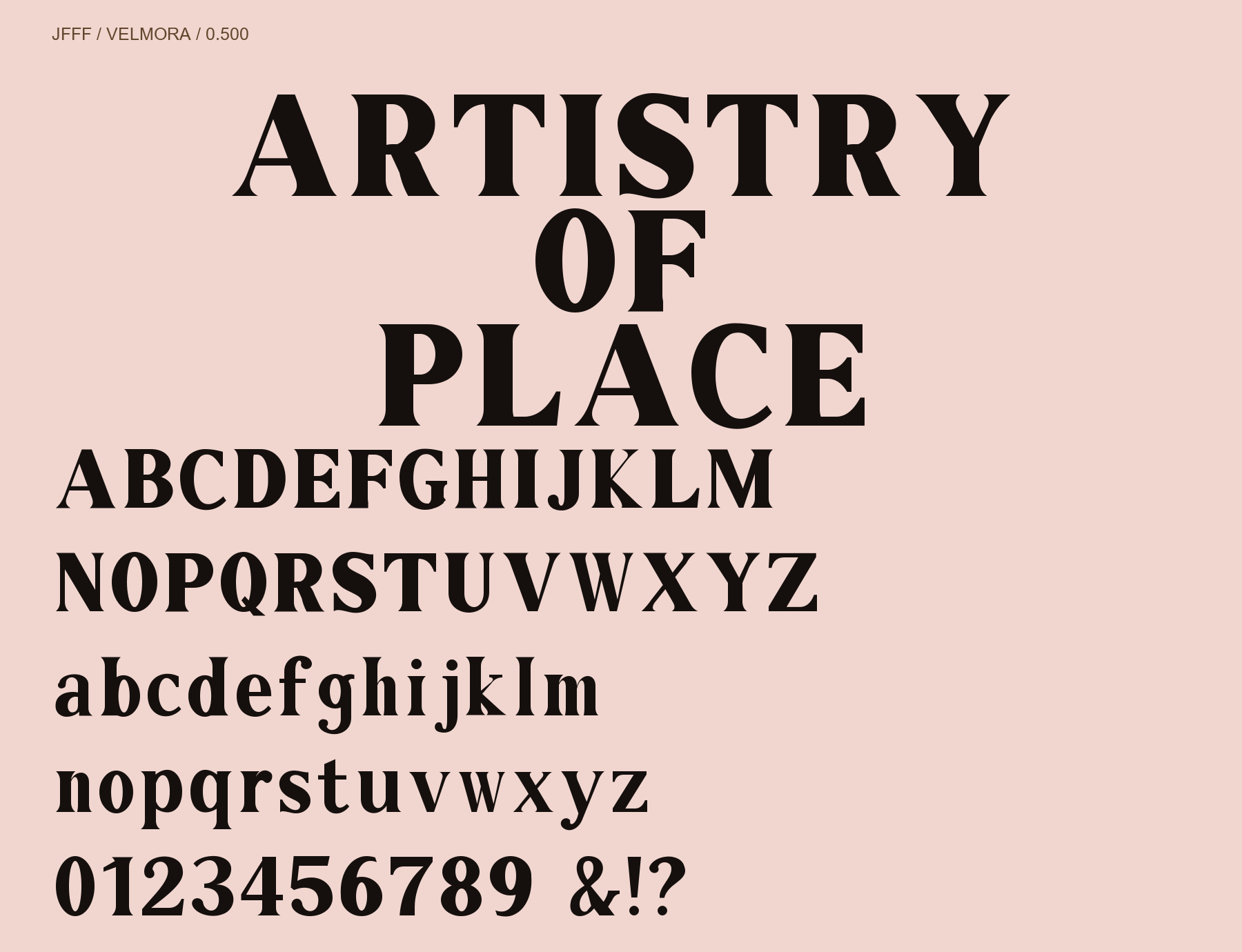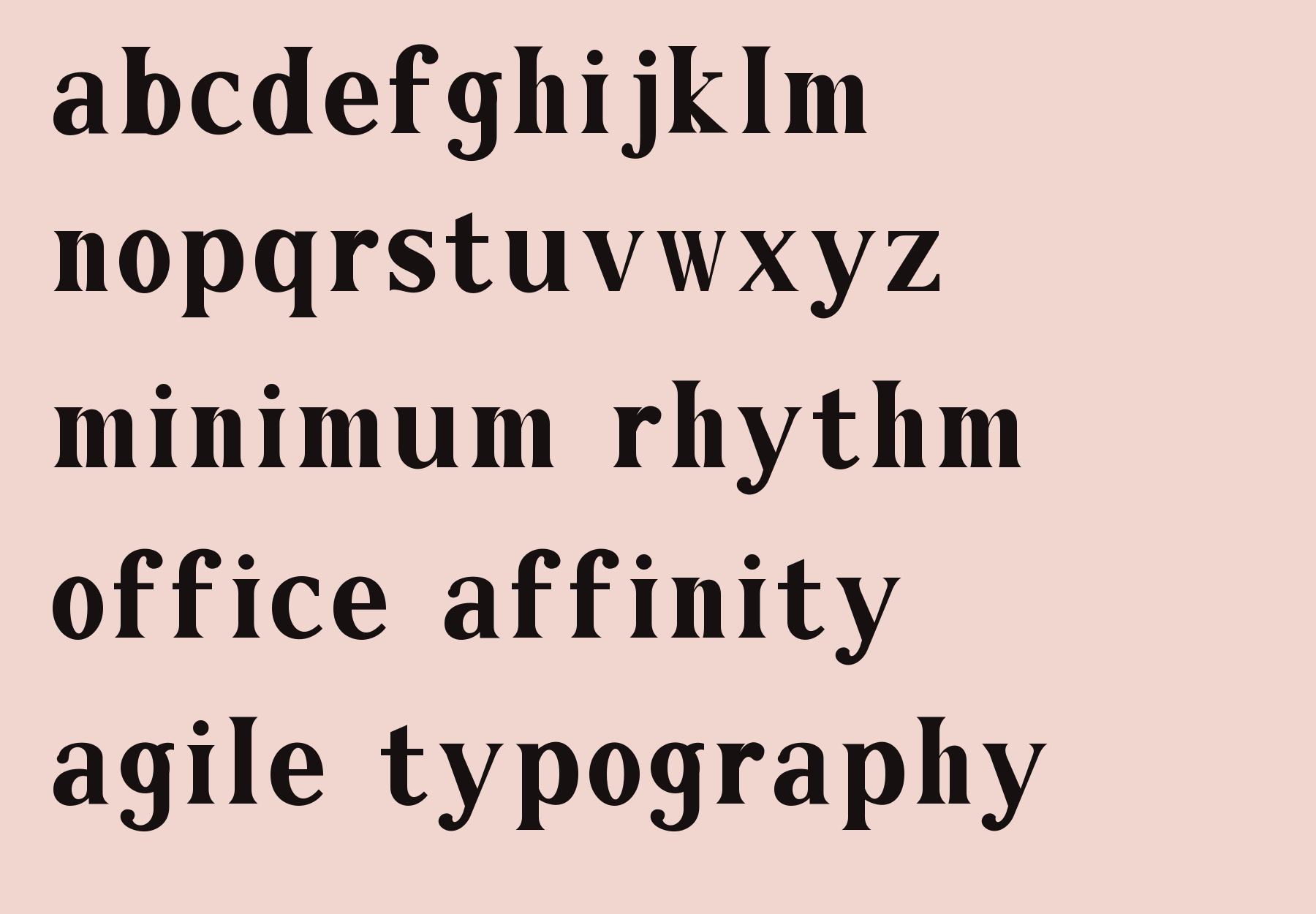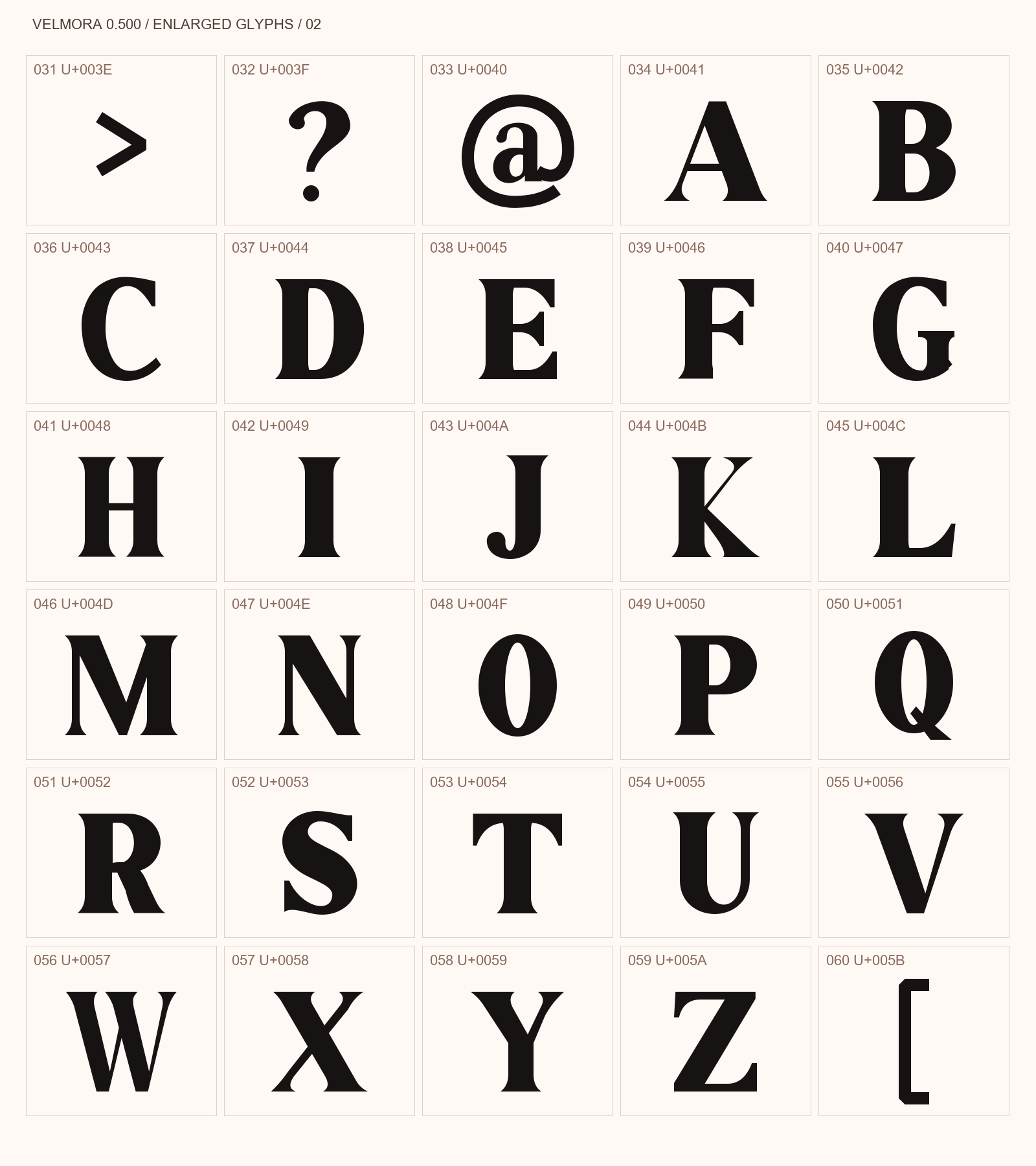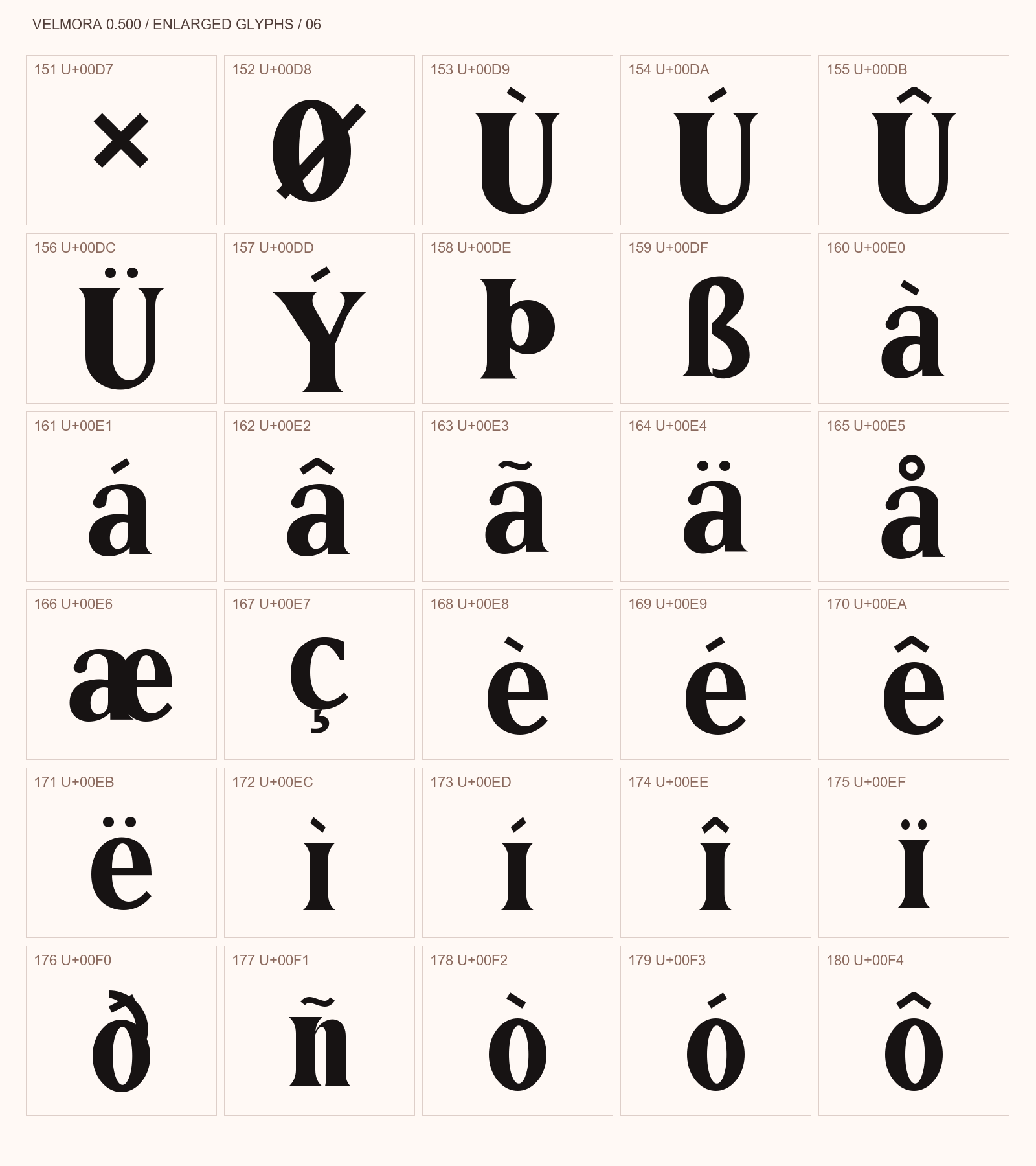
Object Latin
Free high-contrast serif font
Latin only. No Hangul.
Velmora는 무거운 세로획과 가는 연결획, 곡선으로 벌어지는 세리프, 세로로 긴 속공간이 특징인 레트로 디스플레이 세리프 서체입니다. 큰 제목·포스터·짧은 문구에 적합합니다. 버전 0.500 / Regular 1종. 영문 대소문자·숫자·기호·악센트·확장 라틴 330자(공백 포함)를 제공합니다. 한글은 포함하지 않습니다. 소문자의 광학 높이와 어깨 연결, 일부 악센트 두께, 글자별 여백 및 주요 조합 커닝을 조정했습니다. TTF·WOFF2와 SIL OFL 1.1 라이선스를 한 ZIP으로 제공합니다. 무료 사용·수정·재배포가 가능합니다. 24·64·160px에서 비공백 문자 출력 누락이 없음을 확인했습니다. 48px 이상 제목용을 권장하며, 일부 확장 언어의 악센트 관습·전체 커닝 조합·OS 및 브라우저별 출력은 추가 검토 대상입니다.
331 glyphs. Use the character grid and type tester to check the exact characters needed for your project.